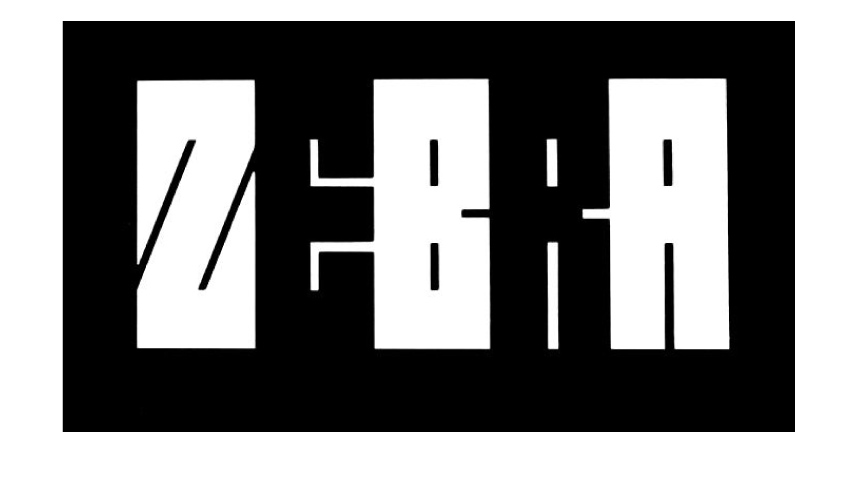
FONDO Y FIGURA
La forma es la apariencia visual de la letra, lo que se percibe como la figura, mientras que la contraforma es el espacio negativo que se encuentra dentro y alrededor de la forma de la letra.
La contraforma es tan importante como la forma misma para la legibilidad, ya que ayuda al ojo a reconocer las letras y las palabras.
Imagen: Logotipo Zebra, Herb Lubalin